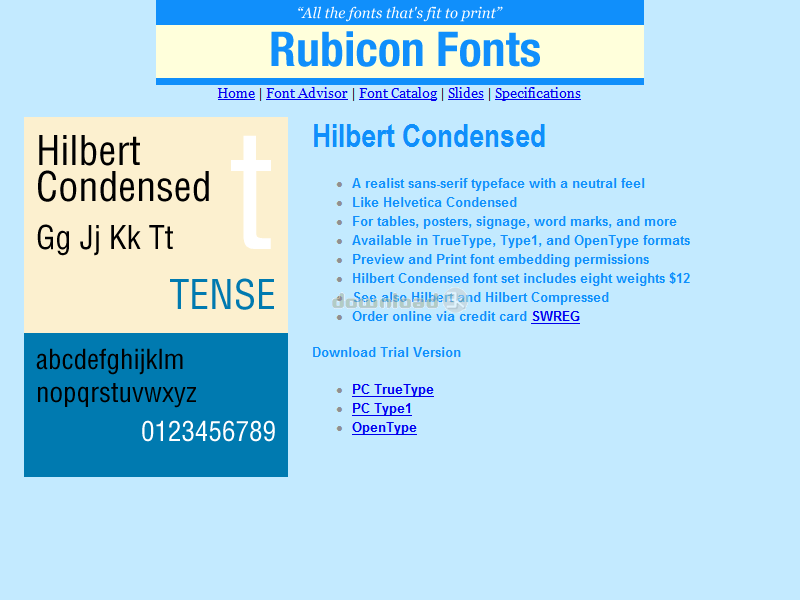
"Realist sans serif font, neutral feel"
Police réaliste sans empattement condensée avec une sensation neutre. Comme Helvetica condensé. Une police de caractères discrète qui semble être partout. Ajustez plus de texte dans des espaces restreints sans perdre la lisibilité. Idéal pour les tables, les affiches, la signalisation et tout autre matériel graphique. Précis et astucieux, métriques de police correspondantes, jeu de caractères standard, paires de crénage. Qualité d'impression professionnelle pour jet d'encre, laser, typographe jusqu'à 3500 dpi. Les acheteurs reçoivent les 8 variantes de police suivantes: Léger, Oblique clair, Normal, Oblique, Gras, Gras Oblique, Extrabold, Extrabold Oblique.Exigences: No special requirements.